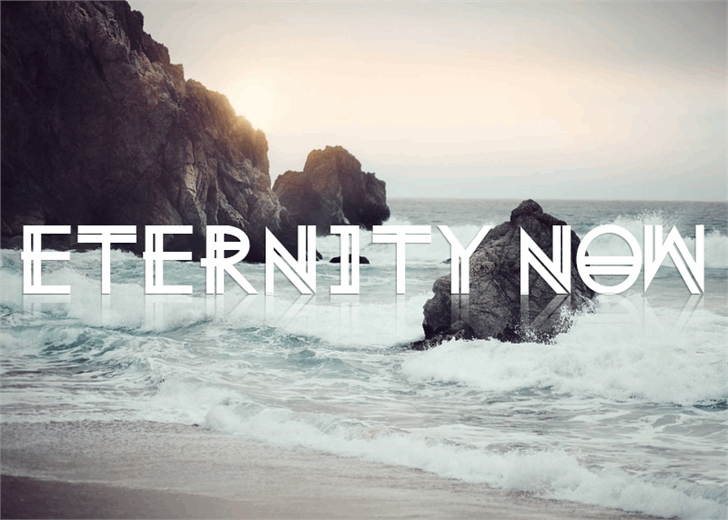
Eternity Now font – Fonte Grátis
Eternity Now font
A fonte Eternity Now é uma exuberante escolha para qualquer projeto que valorize a presença visual forte e vibrante. Trata-se de uma fonte display que traz à tona as emoções e nuances de sua mensagem, oferecendo uma aparição imediata e atrativa. Inspirada no designer Hamilton, esta fonte é notável por suas formas fluidas e detalhes cuidadosamente elaborados, proporcionando um acabamento luxuoso às superfícies digitais. Com Eternity Now, qualquer projeto gráfico ganha um brilho a mais, seja para logotipos poderosos que se destacam na tela ou para design de letras com uma presença sensorial que transmite imediatamente. Essa fonte é perfeita para aqueles buscando uma maneira única e impressionante de comunicar sua ideia. A elegância de Eternity Now combina-se perfeitamente com a versatilidade da tecnologia moderna, tornando-a uma opção ideal não apenas para o design em papel, mas também para criações digitais vibrantes. Seja para criar um slogan memorável ou decorar sua página web, Eternity Now é uma fonte de escolha que transformará qualquer projeto no centro das atenções.